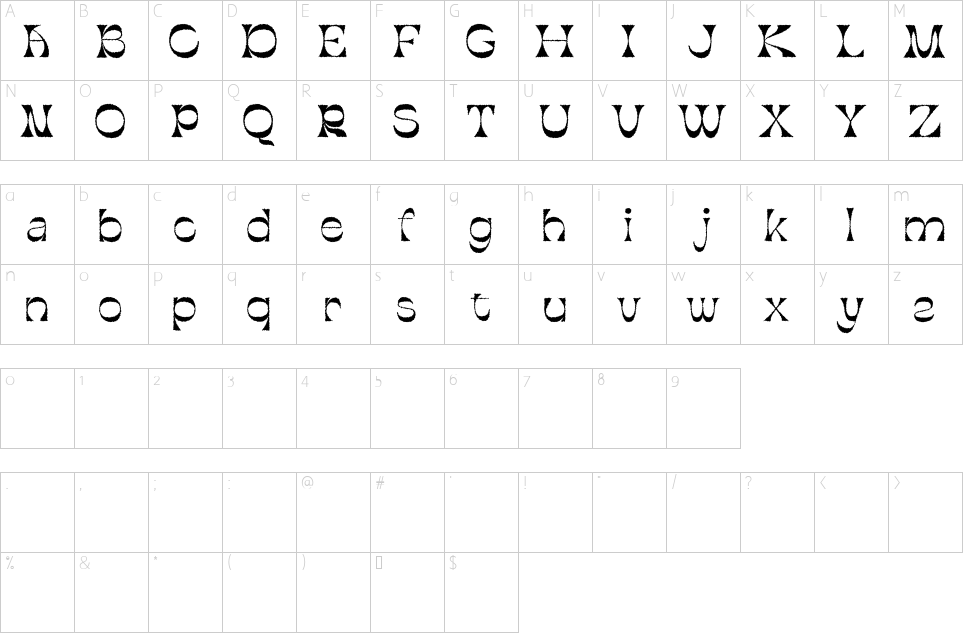
Descubra Abeleo Rough, uma fonte rude e robusta ideal para qualquer projeto que exija um toque casual e distinto. Desenvolvida por Craft Supply Co, Abeleo Rough é perfeita para adicionar um toque arredondado e um pouco de personalidade a seus materiais digitais. Seja em seu website, seu material de marketing ou até mesmo em seus materiais de impressão, Abeleo Rough garante que sua mensagem seja memorável e chamativa. Com uma aparência que combina elementos de estilos clássicos e modernos, Abeleo Rough oferece uma versatilidade incrível, permitindo que você personalize sua identidade visual conforme necessário. Se você está buscando uma fonte que ofereça um pouco de profundidade e uma aparência um pouco menos formal, Abeleo Rough pode ser o recurso perfeito para você. E, como uma das muitas fontes gratuitas disponíveis na biblioteca 1001 Free Fonts, Abeleo Rough está sempre disponível para download. Com uma facilidade de uso fácil e uma aparência que se adapta a qualquer projeto, Abeleo Rough é uma ótima escolha para qualquer designer ou criador de conteúdo.